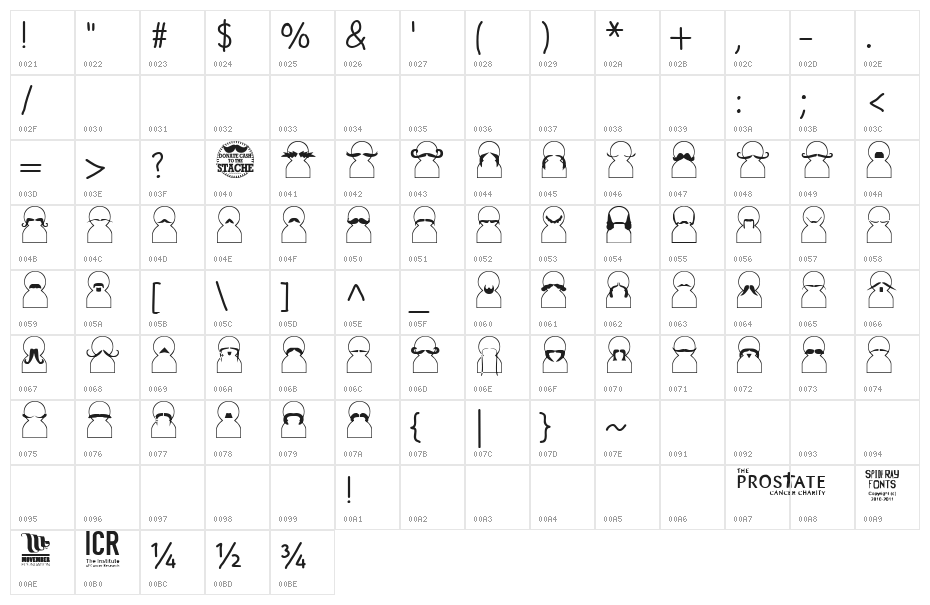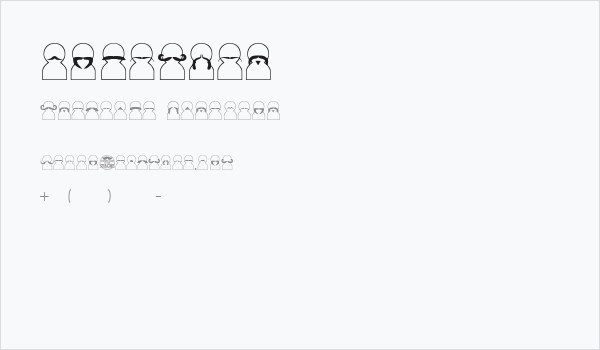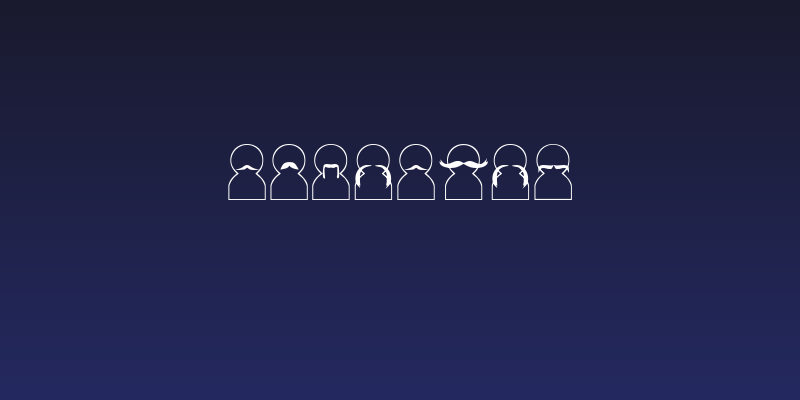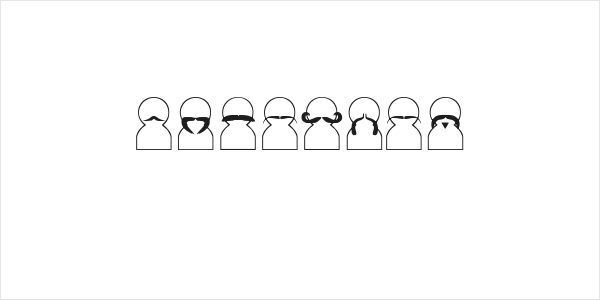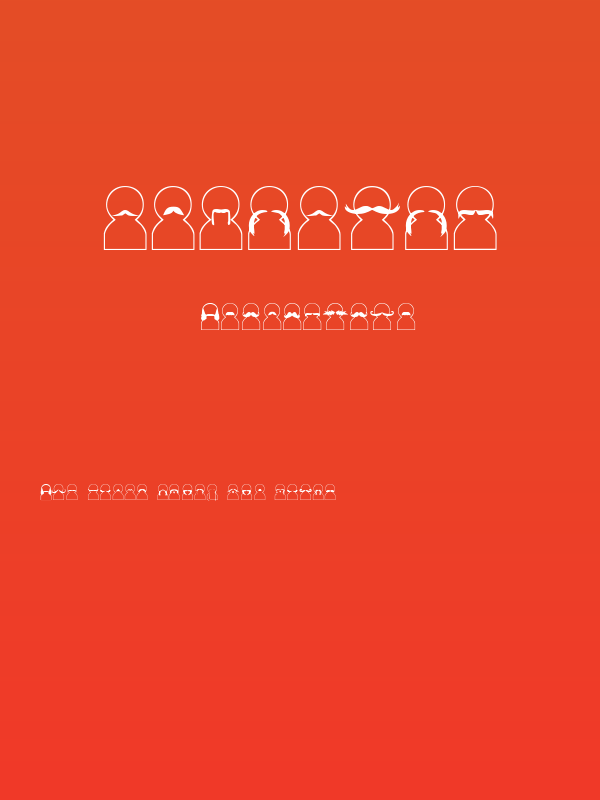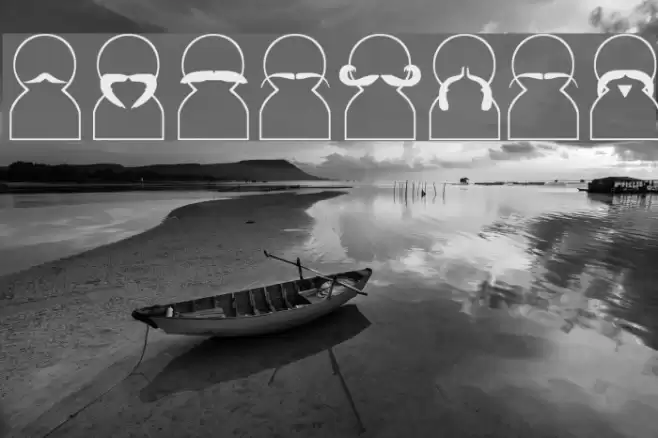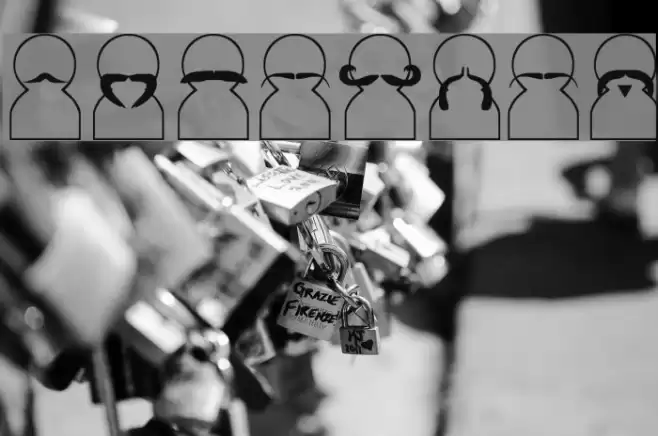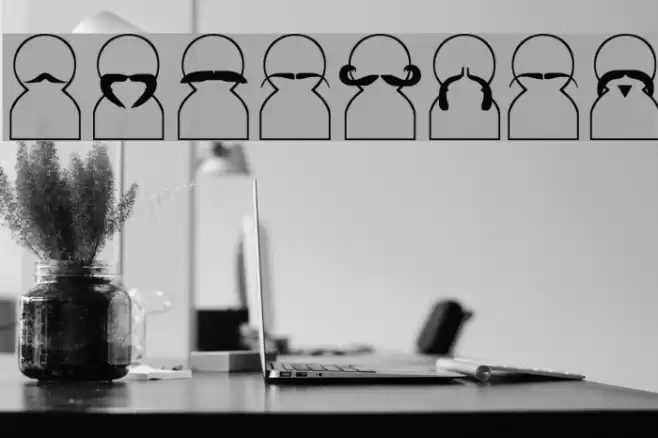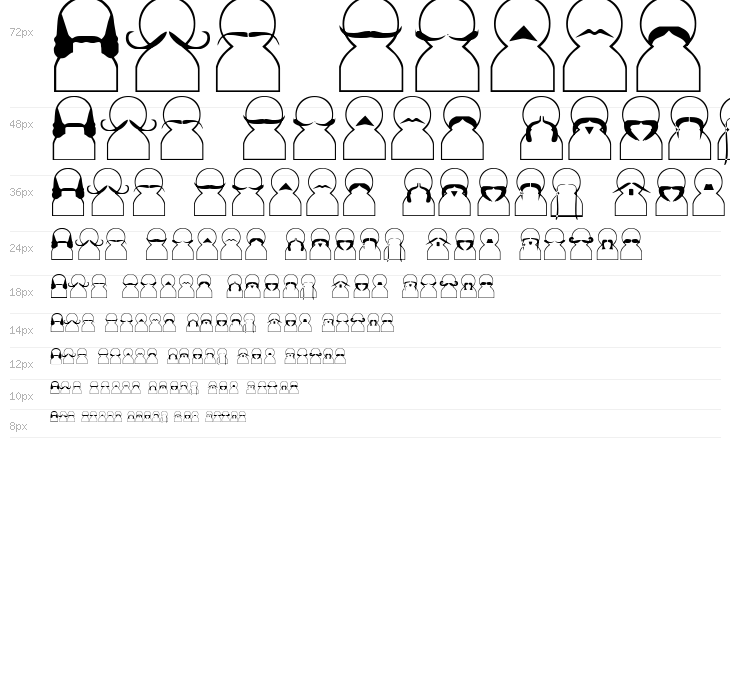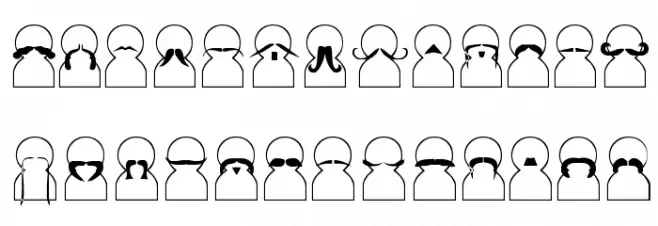
Movember Font
| النمط العام | Playful |
| حالة الاستخدام | Logos, Headlines, Posters |
| مشاريع مقترحة | Ideal for event posters, themed invitations, social media graphics, and awareness campaigns related to Movember. |